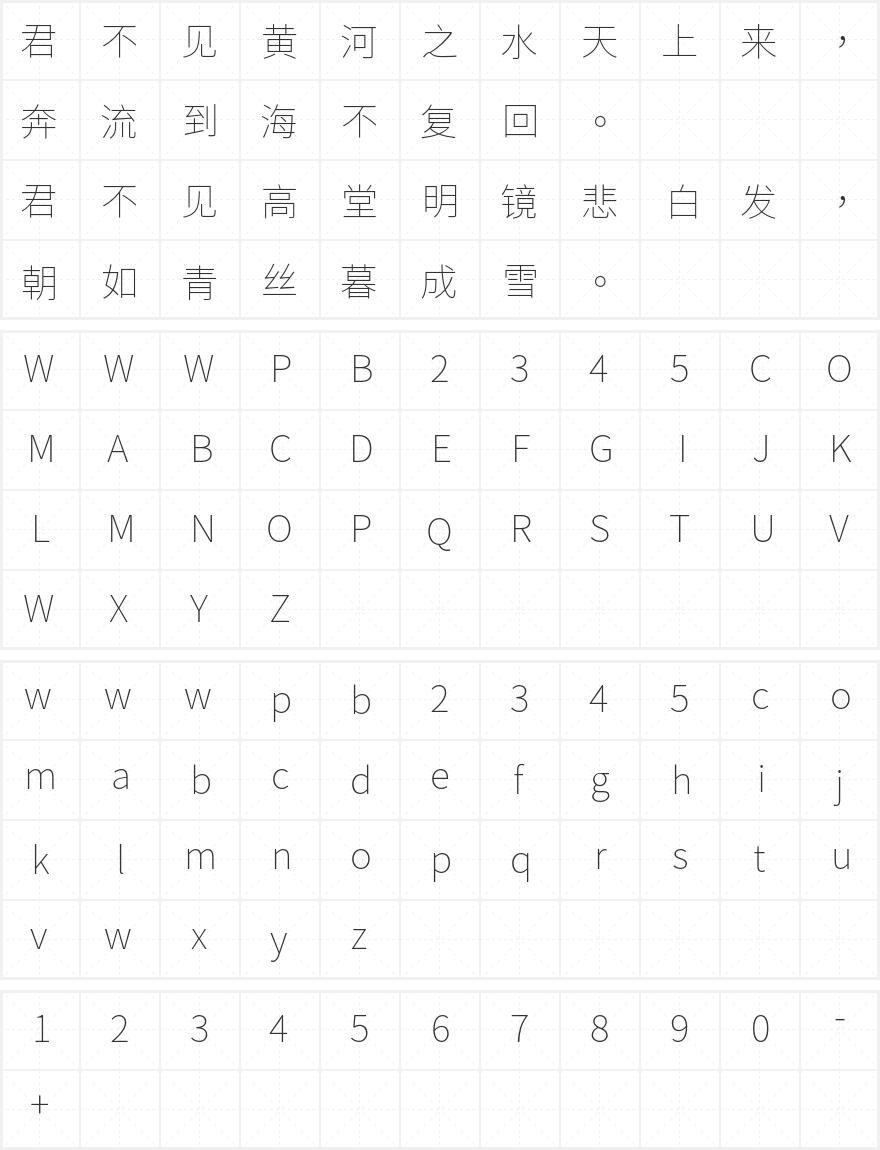
思源黑体 SourceHanSansSC-ExtraLight
思源黑体 ExtraLight
思源黑体 SourceHanSansSC-ExtraLight 字体全解析
思源黑体 SourceHanSansSC-ExtraLight 是由 Adobe 与 Google 联合打造的思源黑体系列中的极细字重变体,专为追求轻盈视觉效果与清晰可读性的场景设计,是该系列覆盖 "特幼至特粗" 七级字重体系中的轻量化代表。其名称中 "SC" 代表简体中文版本,"ExtraLight" 明确标示其极细的笔画特征,在 Google 版本中对应名称为 "Noto Sans CJK Thin"。
核心设计特征
1. 极细笔触与视觉质感:作为思源黑体中最轻盈的字重,其笔画纤细却不失张力,线条呈现俐落无垢的设计风格。延续了思源黑体 "重心置中却显偏低、中宫开阔、字面率大" 的家族基因,字符布白匀称秀美,负空间分布均衡,既保留了无衬线字体的现代简洁,又暗含人文温度。
2. 多语言字符集支持:单字体文件包含超过 65535 个字形,达到 OpenType 格式字符量上限,全面覆盖简体中文(含常用字与生僻字)、繁体中文、日文、韩文等东亚语言,同时兼容拉丁语、希腊语、西里尔文等西方字符集。针对不同地区的用字习惯保留必要差异,可实现多语言排版的风格统一。
3. 跨场景适配优化:虽笔触极细,但经过屏幕显示专项优化,在手机、平板等小尺寸设备上仍能保持清晰易读性。其设计充分考虑像素差异带来的视觉变化,即使在不同亮度背景下,也能减少光晕模糊问题,兼顾电子显示与印刷输出的双重需求。
适用场景与设计价值
凭借极细笔触的视觉特性,SourceHanSansSC-ExtraLight 在多类场景中展现独特优势:
• 电子阅读与长文本排版:轻盈的笔画能降低长时间阅读的视觉疲劳,尤其适合电子书正文、手机 APP 内文、网页长段落等屏幕阅读场景;
• 轻量化设计场景:适用于品牌形象中的辅助文字、海报副标题、杂志内页注解等需凸显层次感的设计,与粗体标题搭配可形成强烈视觉对比;
• 精细排版需求:在数据可视化、信息图表、办公文档等需要密集呈现文字的场景中,其开阔的字符间距能避免排版拥挤,提升信息传递效率;
• 跨媒介适配场景:从移动端界面的菜单文字到印刷品的雅致注解,均能保持一致的轻盈风格,适配从屏幕到纸张的全场景应用。
与家族其他字重的区别
作为思源黑体七级字重体系的起点,SourceHanSansSC-ExtraLight 与其他字重形成明确功能划分:相较于 Light 字重更显纤细,无 Regular 字重的标准视觉重量,也区别于 Bold、Heavy 等粗体的强调属性,专注于 "轻量化表达" 的细分需求。这种精细的字重梯度设计,让设计师可根据内容层级、视觉重点与媒介特性,实现从正文到标题的无缝风格衔接。